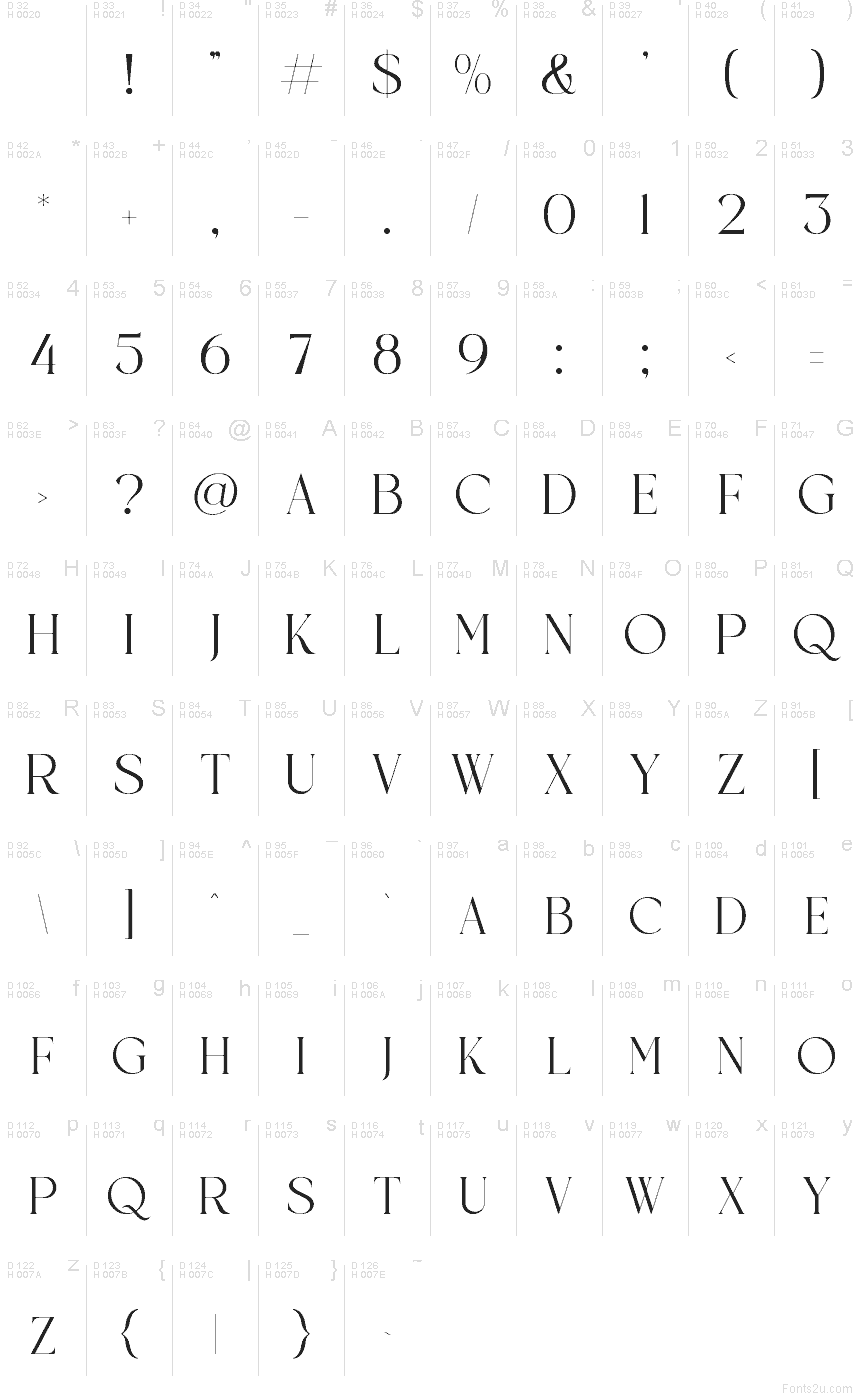
Sparkle Passion od TimelessType.co je bezplatné serifové písmo s vysokým kontrastem a vytříbeným redakčním stylem. Velká písmena kombinují vlasové spoje a dlouhé, rozmáchlé křivky s ostrými, precizními řezy, díky čemuž působí písmo elegantně a rozhodně, přesto ne křehce.
Hodí se pro branding v oblasti krásy a šperků, pro titulky časopisů, obaly, pozvánky a vývěsní štíty butiků, kde je žádoucí trochu dramatu. Jako bezplatné písmo se také skvěle hodí na titulní strany, kartičky s názvy a monogramy, protože písmena dodávají i krátkým slovům vysoký, zářivý vzhled.
Sparkle Passion